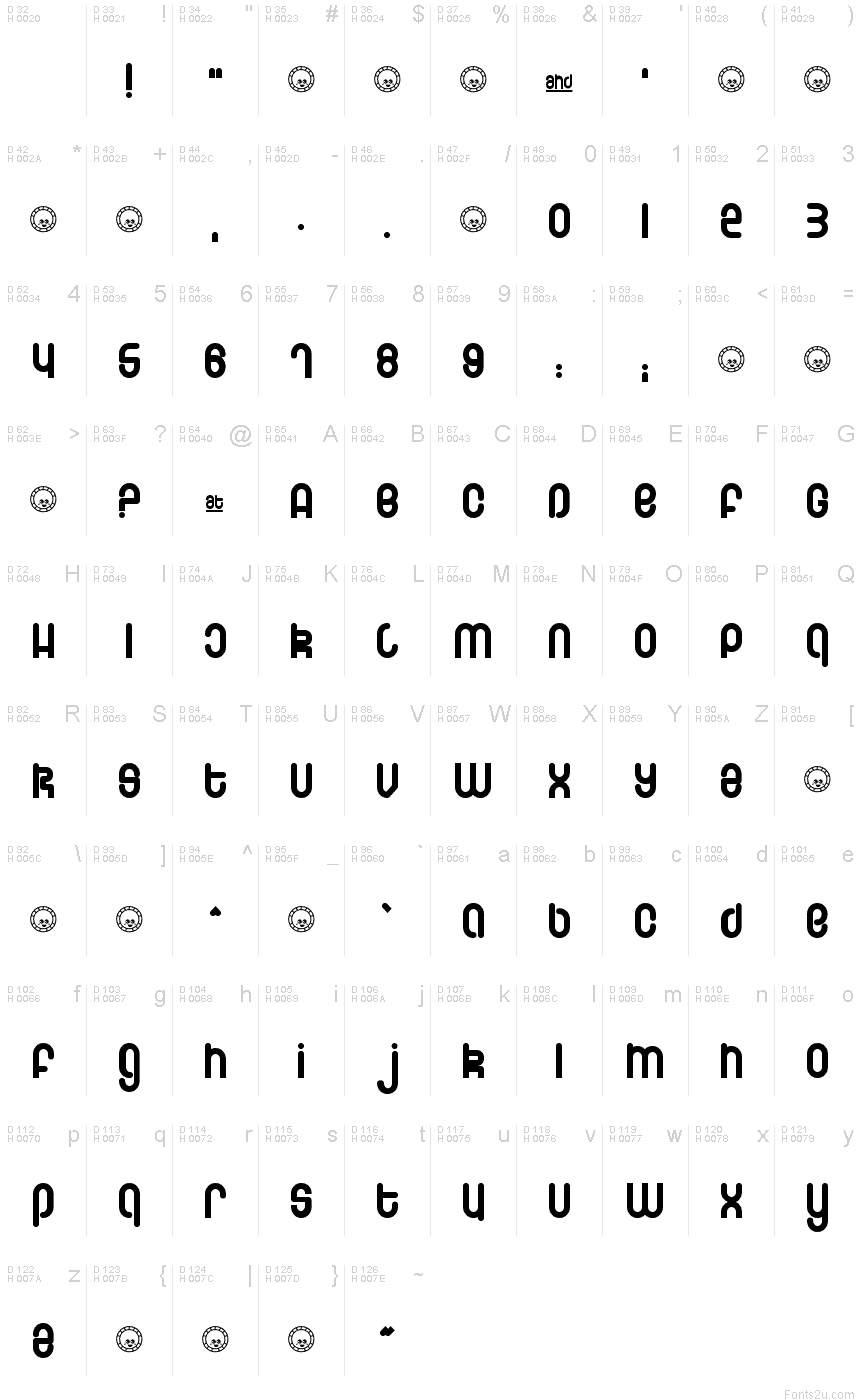
Schmotto od Font"a"licious Fonts to darmowy, nowoczesny krój displayowy o zaokrąglonych kształtach i miękkim, niemal bąbelkowym rytmie. Litery opierają się na grubych kreskach, głębokich łukach i tępych łączeniach, dzięki czemu napis sprawia wrażenie zabawnego i lekko retro, a nie wygładzonego.
Idealnie pasuje do nagłówków na plakatach, oprawy muzycznej, młodzieżowego brandingu, opakowań i szkiców logo, gdzie tak bardzo zakrzywiona czcionka może nadać ton całej kompozycji. Ze względu na pełne i proste formy, Schmotto świetnie sprawdza się również w krótkich tekstach na okładkach, planszach tytułowych i wyrazistych inicjałach, które mają mieć przyjazny, masywny charakter.